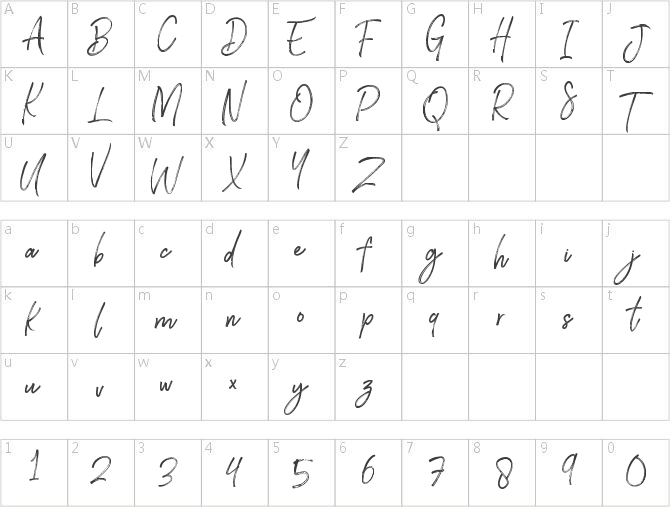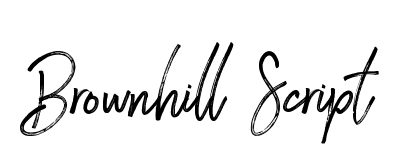
Brownhill Script
Brownhill Script介绍
Brownhill Script字体Brownhill Script Regular字库是一款让人赏心悦目、百看不厌的英文字体,适合各类广告和产品包装设计应用,字体大小0.68MB,格式为otf字体,上传用户是后天的昨天,作者/版权方为Brownhill